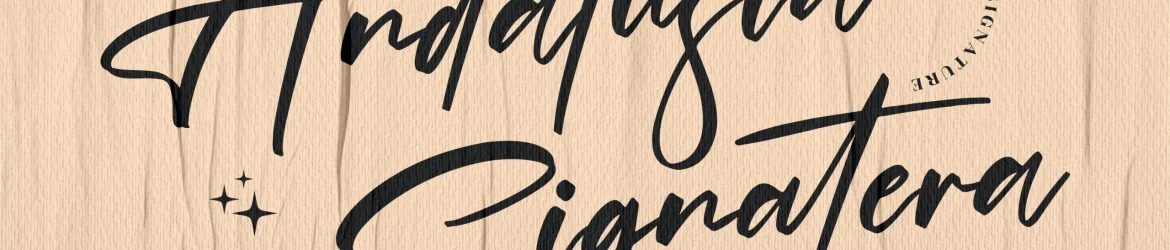
Andalusia Signatera Font – Download Grátis
A Andalusia Signatera Font é uma elegante escolha para designers que buscam dar um toque premium a seus projetos de marca ou design de produtos. Sujeitável a uma variedade de aplicativos, incluindo logotipos, identidades visuais, embalagens de produto, etiquetas e até mesmo as capas de livros, é perfeita para quem busca um toque sofisticado em seus projetos. Com seu estilo levemente à mão escrita, essa fonte oferece uma personalidade única que pode fazer sua marca se destacar. Ideal tanto para designers profissionais quanto para iniciantes, a Andalusia Signatera Font traz um ar de sofisticação e criatividade, tornando-a uma escolha inteligente para projetos especiais ou até mesmo simples itens de lazer como tênis de sapato ou sacolas de compras. Com sua capacidade de adaptar-se a uma variedade de formatos, ela também é excelente para criar um design impecável em qualquer projeto que você possa estar trabalhando. A versão handwritten deste font foi criada por Perspectype, designer renomado da área de grafismo, e oferece uma maneira única de dar aos seus projetos uma identidade inovadora. A escolha da Andalusia Signatera Font não apenas tornará seus designs mais atraentes, mas também adicionará um toque único que pode se destacar em um mundo repleto de opções design.